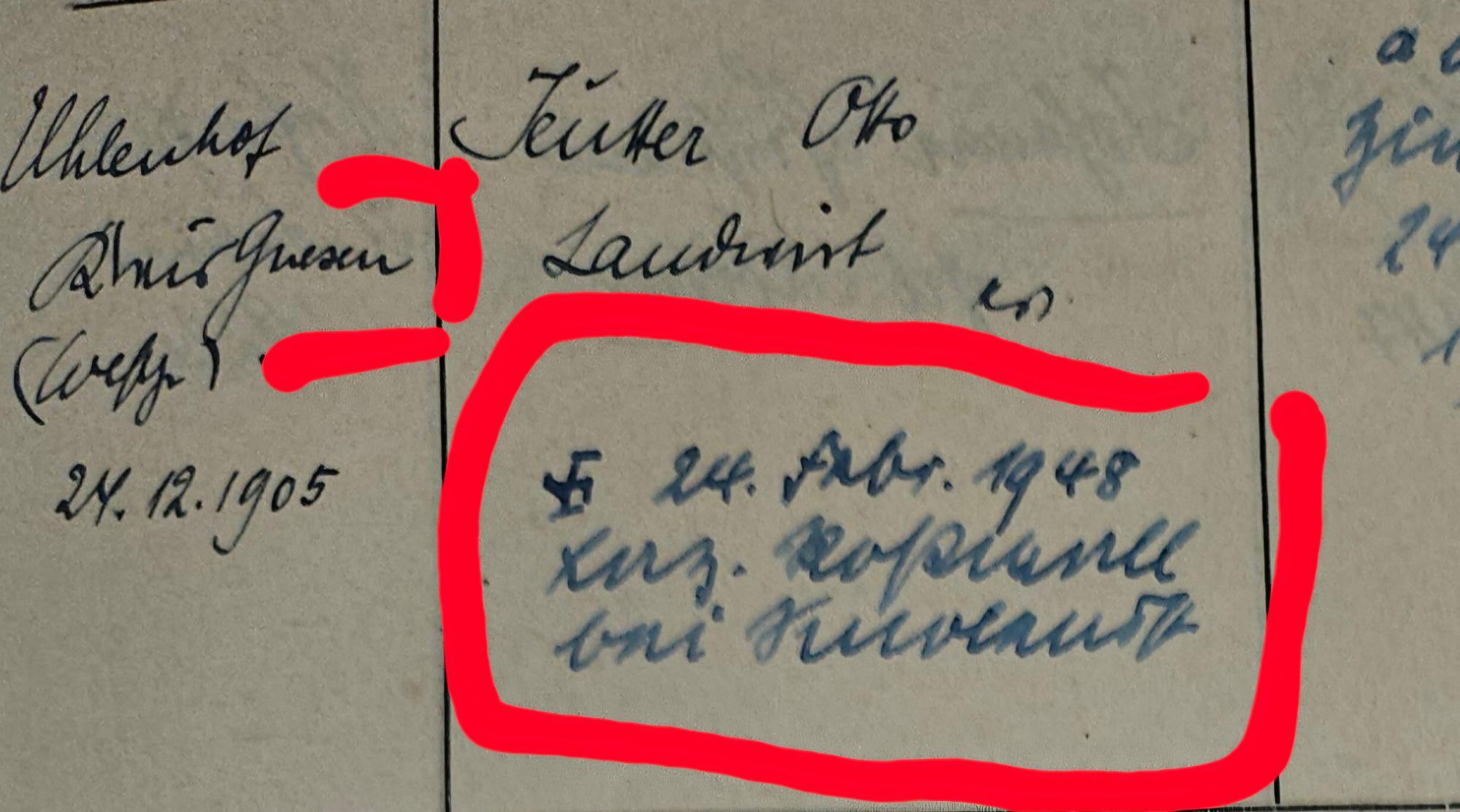
Ich hatte heute Gelegenheit in alten Kirchenbüchern zu stöbern. Leider gibt es Eintragungen, bei denen auch Transkribus nicht weiterkommt. Gibt es eine empfehlenswerte Software zum Entziffern von Sütterlin?
Hier steht vermutlich in welchem Gefangenenlager in Russland mein Opa gestorben ist.
für den linken Teil bräuchte man etwas Kontext.
der Sterbeeintrag lautet:
† 24. Febr. 1948
Laz[arett]. Roßlawl
bei Smolensk
Genaugenommen handelt es sich um deutsche Kurrent, nicht um Sütterlin. Die Idee mit der Software würde ich verwerfen.
… und ringsum ist auch etwas Lateinische Schreibschrift beigemischt, das macht's auch nicht einfacher.
Das ist Kurrent?  Das heißt ich kann aufhören Sütterlin zu lernen? 😆
Oder gleich beides Lernen?
Ich habe auch gemerkt, dass teilweise schon Lateinische Schrift geschrieben, oder noch schlimmer mit Kurrent vermischt ist. Das ist echt nicht einfach.
das stimmt.
Die Sütterlinschrift ist eine Variante der deutschen Kurrentschrift.